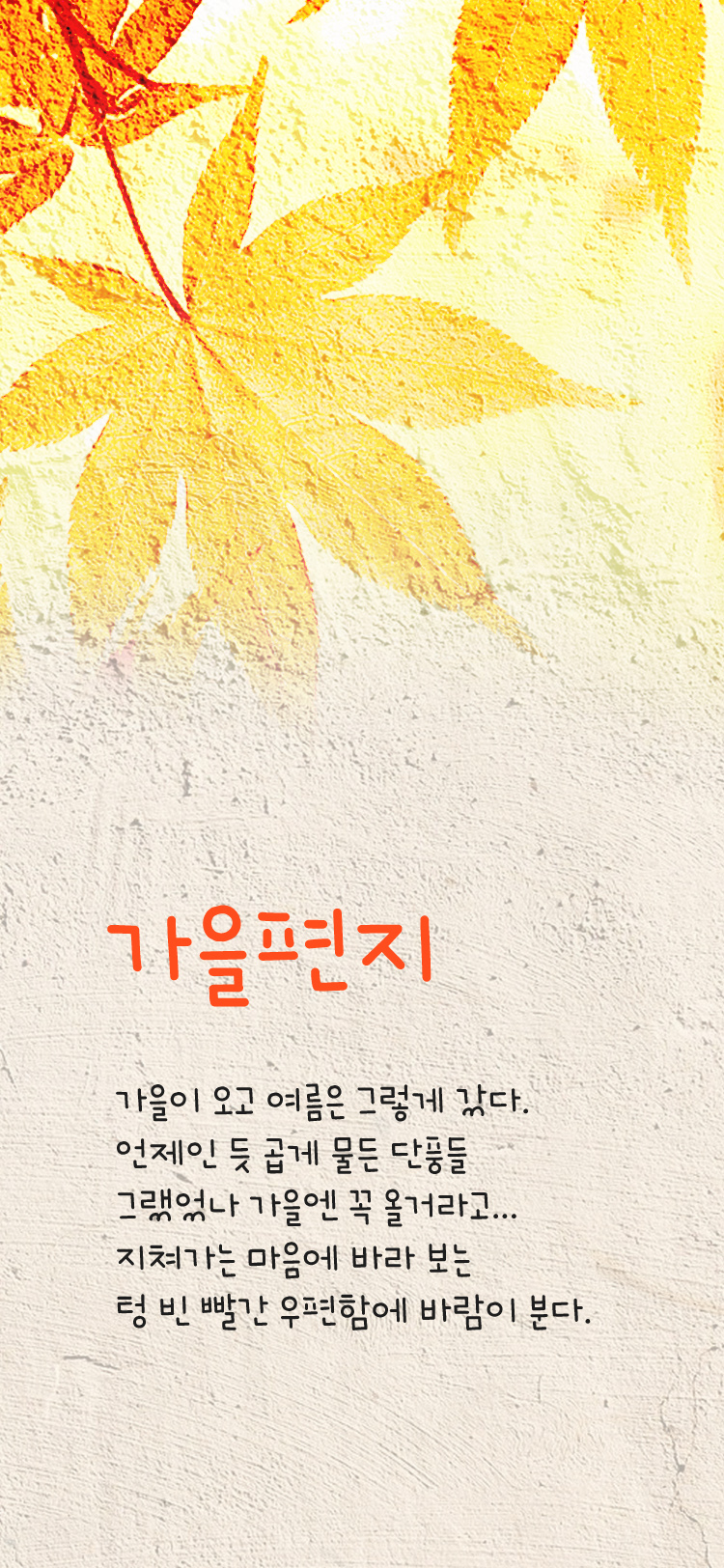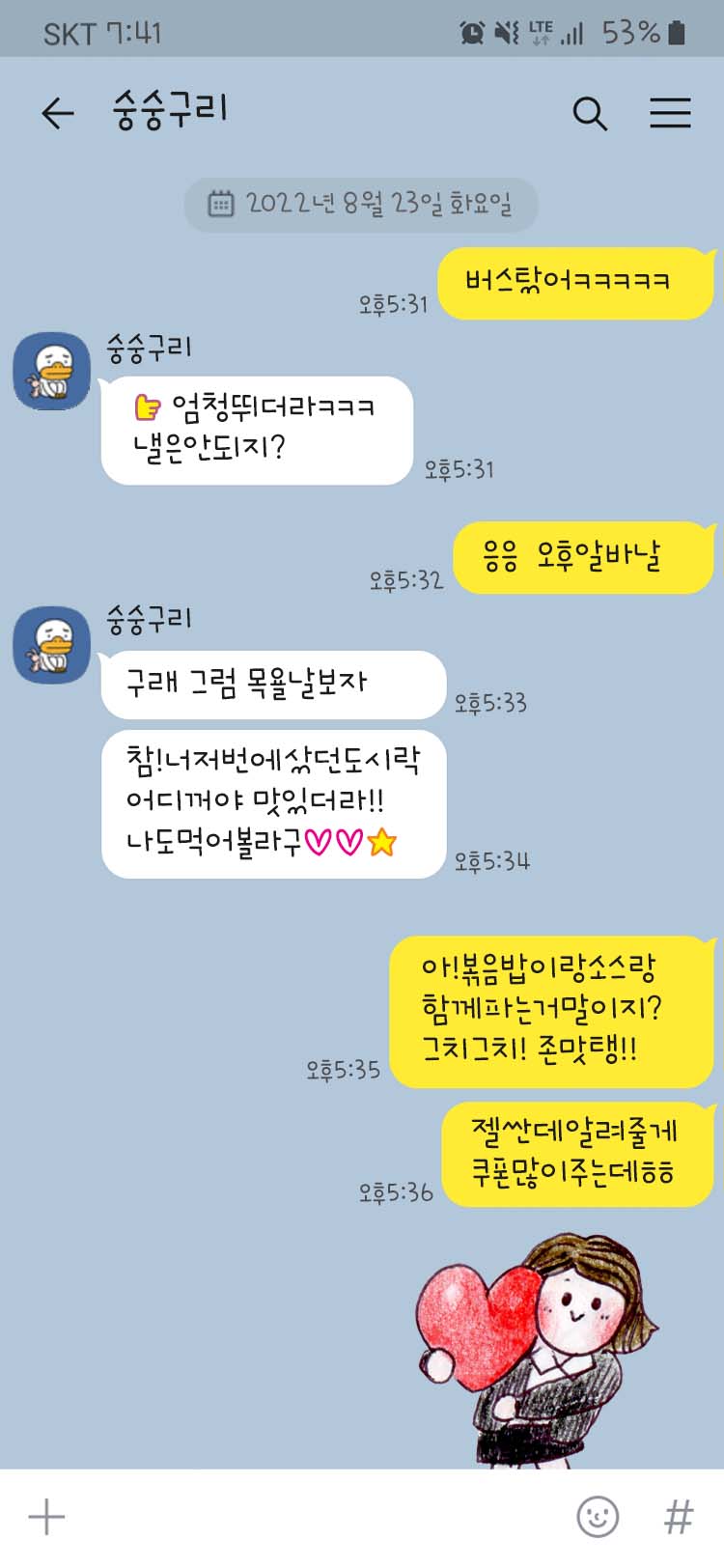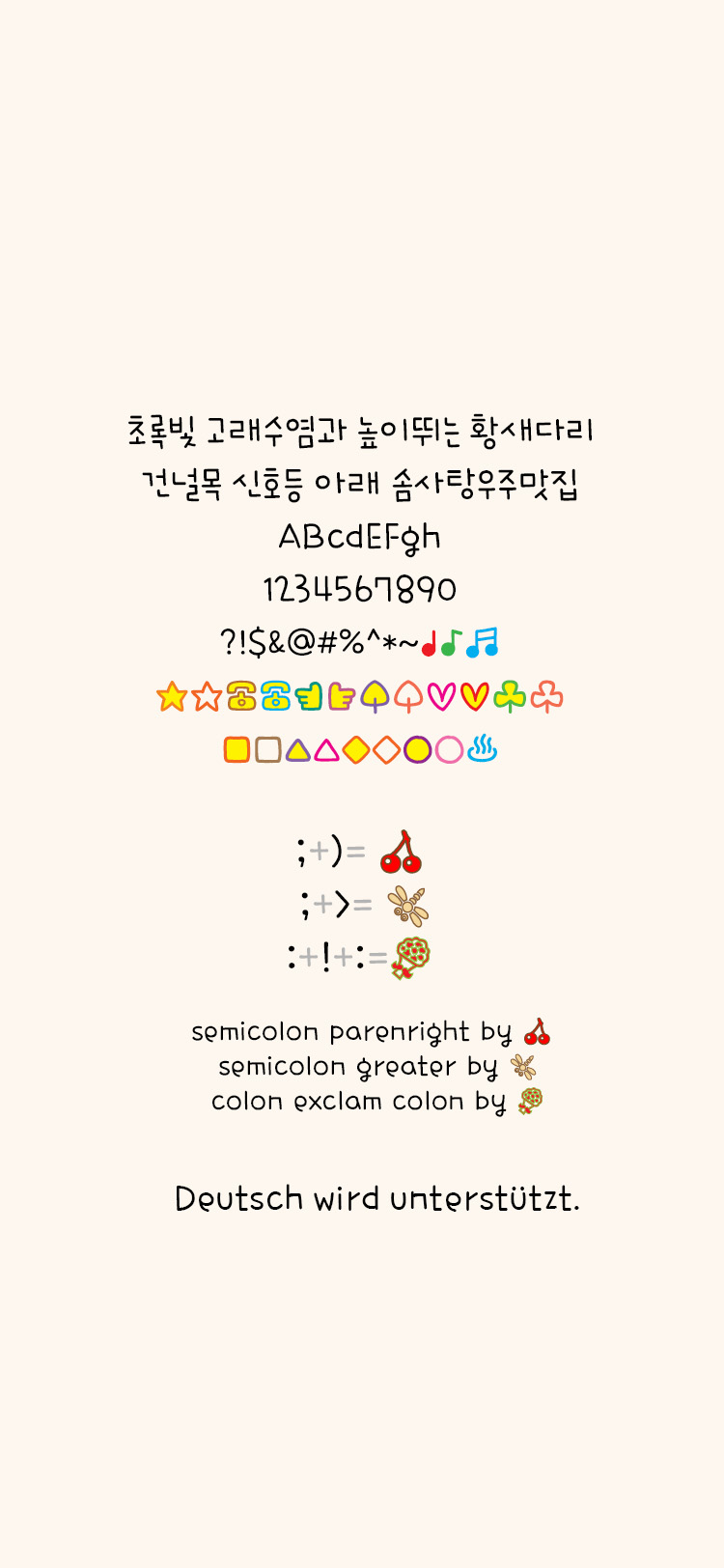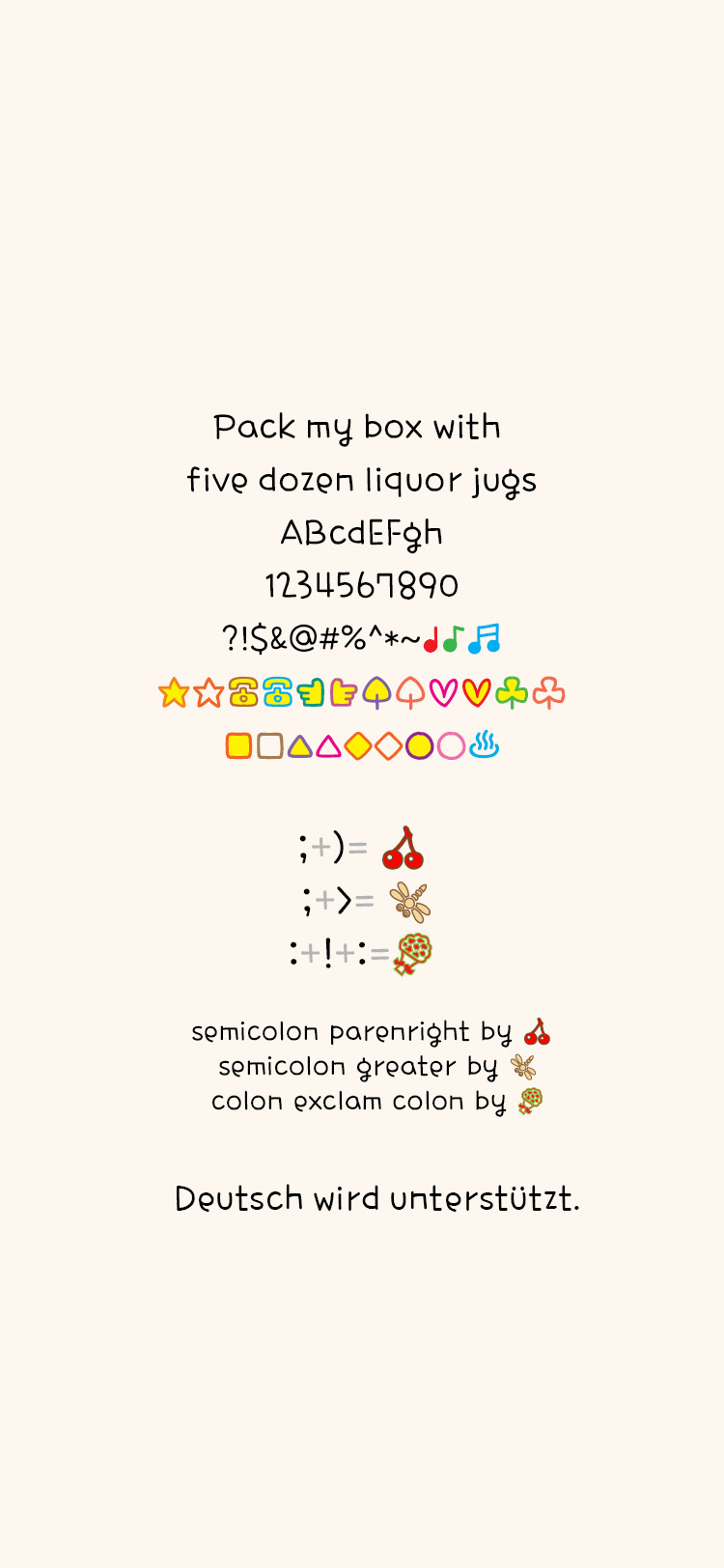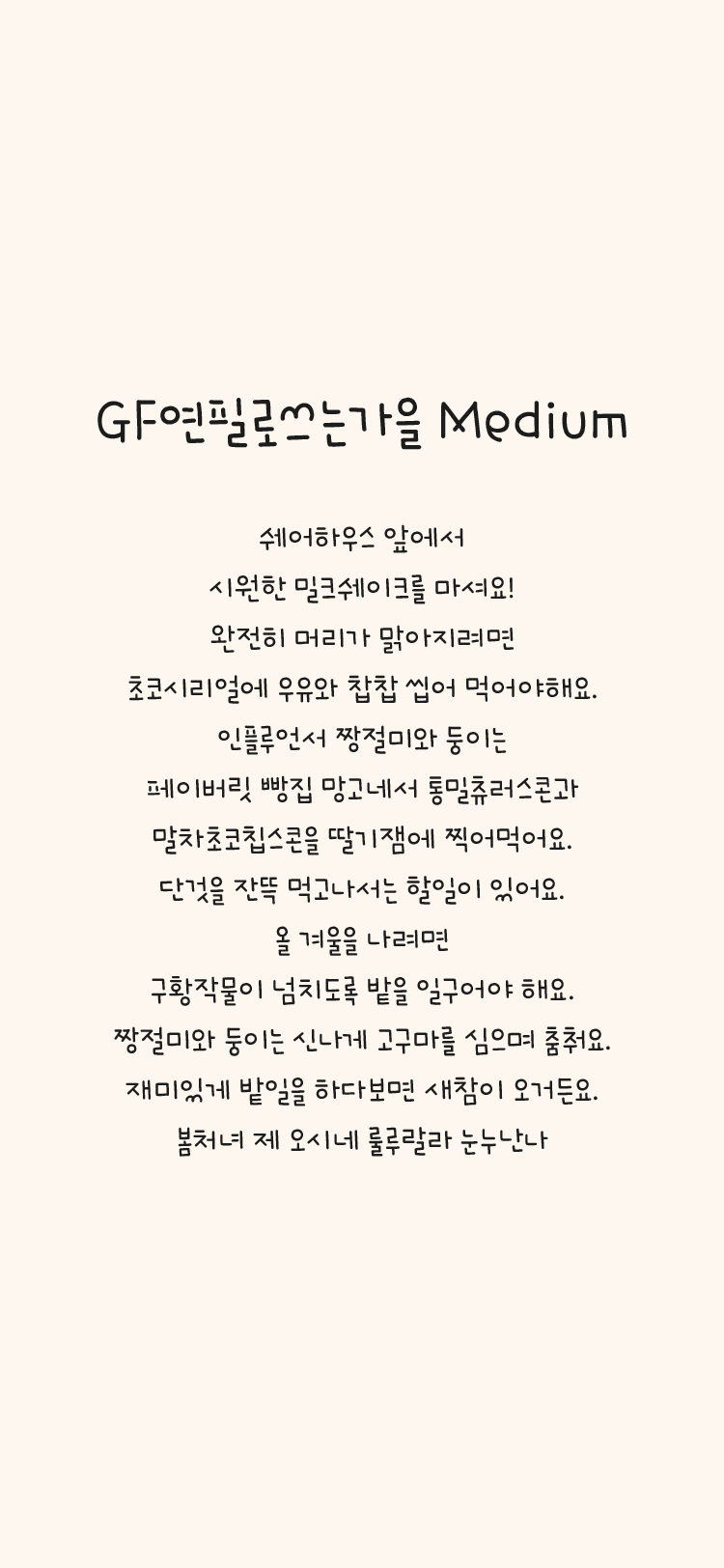
GF 연필로쓰는가을 M Medium
곱게 물든 나뭇잎, 파란 하늘에 솜사탕 같은 뭉게구름이 떠다니는 가을을 모티브로 제작 되었습니다. 귀여운 자소들은 아기자기한 조판을 연출하여 보고 치는 즐거움이 풍성한 글꼴 입니다. 초성, 종성의 'ㅆ'은 뭉게구름과 산을 표현하여, 자연과 글꼴의 조화를 이루어 보았습니다. 일부 컬러 약물과 딩벳이 지원 됩니다.
semicolon parenright by 체리
semicolon greater by 잠자리
colon exclam colon by 꽃다발